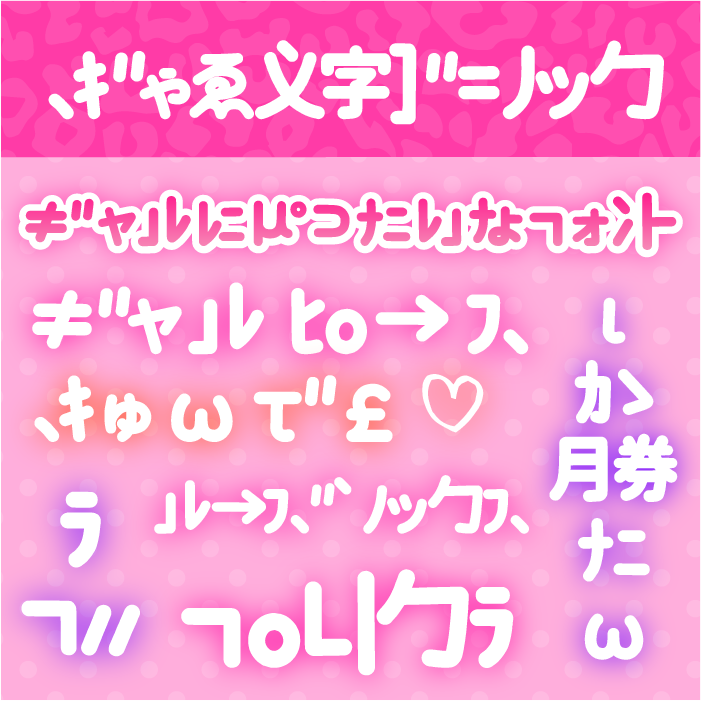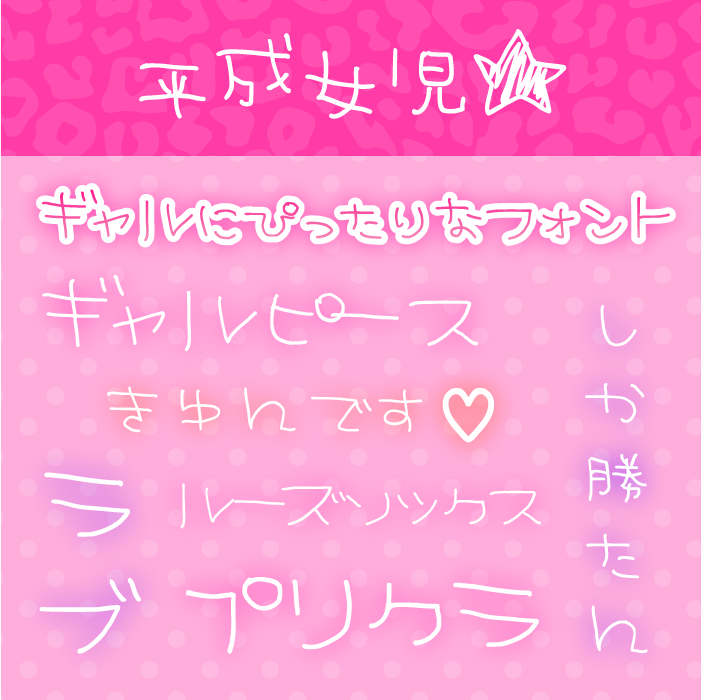
今回は、テンション高めで派手かわいい!そんな「ギャル」な世界観にぴったりのフリーフォントをご紹介します。
ギャルといえば、ルーズソックスにプリクラ、ガラケー時代のデコ文字、そして自己流を貫くスタイルが魅力の文化があります。
派手でゴージャス、だけどどこか愛嬌があって、見る人の心をワクワクさせる不思議なパワーがあります。そんなギャルマインドを詰めこんだような、キラキラ感・勢い・ちょい毒っ気のあるフリーフォントをまとめてみました。
「ギャル」におすすめのフォントまとめ
以下のサンプル画像は本記事で紹介している一部ですが、派手でゴージャス、だけどどこか可愛らしい「ギャル」そんなフォントデザインをまとめてみました。
モッチーポップ
モッチーポップフォントは、サインペンで書いた文字を下敷きにしてトレースしてパス化している文字なので、女性的な丸みがある可愛いギャルっぽさがあるフォントとなっています。
ポプらむ☆キウイ
ポプらむ☆キュートフォントは、コミカルな仕上がりに作られたフォントになっています。平成レトロ感を感じる可愛らしいデザインです。
源暎ぽっぷる
源暎ぽっぷるフォントは、手書き風な曲線が可愛いらしいPOP体風仮名のゴシック体フォントです。ギャル文字っぽく、コロコロと丸っこい雰囲気がとてもかわいらしいです。
鬼淀ギャル
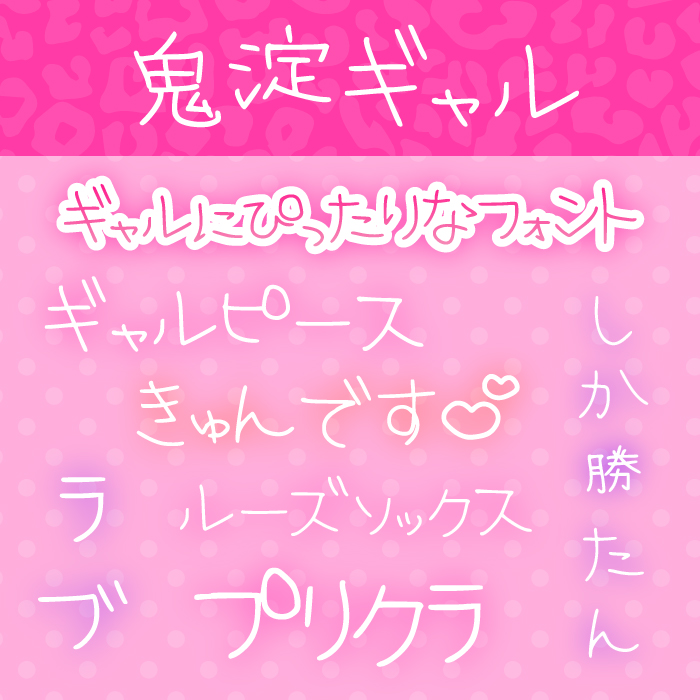
鬼淀フォントは、ギャル漫画家Vtuber「鬼淀」さんによる下手かわギャル字フォントです。ギャルが書いた文字のようにゆるくて、丸みがある文字がとっても可愛らしいです。
はる手書きフォント
はる手書きフォントは、少し縦長フォルムが特徴的なナチュラル系の手書きフォントです。
プリクラ文字などの雰囲気を出すにはぴったりなフォントです。
にゃしぃフォント
にゃしぃフォントは、手書き風の丸文字フォントが柔らかい親しみやすく、ギャル文字の雰囲気のあるフォントとなっています。
まきば
まきばフォントは、小ぶりの可愛らしさと、大人っぽい可愛らしさを兼ね備えた手書きフォントです。
はちまるポップ
はちまるポップ(Hachi Maru Pop)フォントは、平成初期に流行した丸文字にインスパイアされて、現代風にアレンジされたデザインの丸文字系フォントです。平成ギャル感を感じるフォントとなっています。
めもわーる
めもわーるは、ファンシーで可愛らしくインパクトのあるレトロポップなフォントです。Memoir(メモワール)はフランス語で記憶や思い出とのことです。